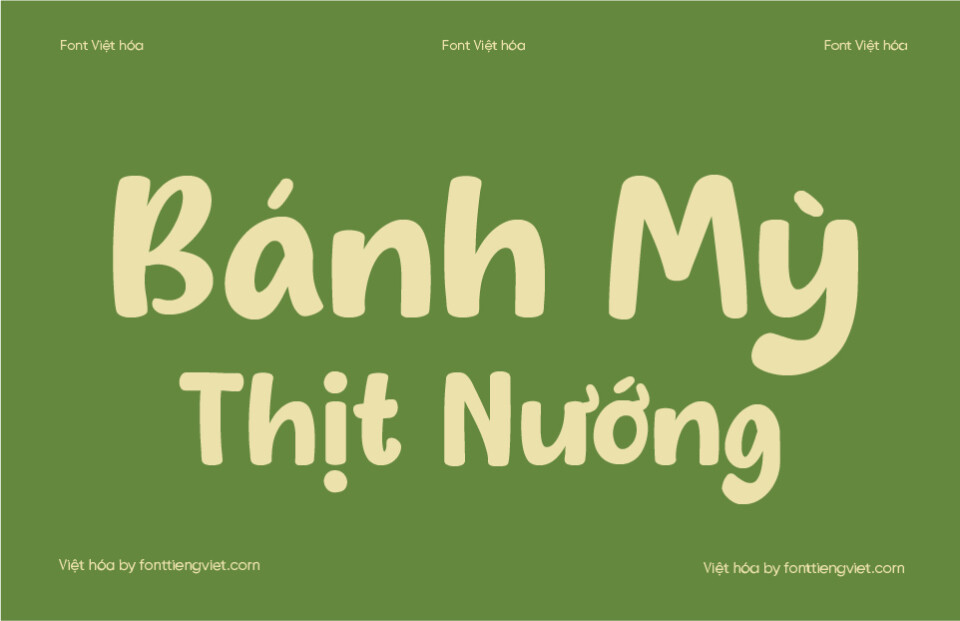
Font Việt hóa 1FTV VIP Season Prime Đẳng Cấp Cho Thiết Kế Chuyên Nghiệp
Giới thiệu về Font Việt hóa 1FTV VIP Season Prime
Trong thế giới thiết kế đồ họa hiện đại, việc lựa chọn một Font Chữ phù hợp đóng vai trò quyết định đến tính thẩm mỹ và thông điệp của sản phẩm. Font Việt hóa 1FTV VIP Season Prime là một bộ phông chữ cao cấp, được tinh chỉnh kỹ lưỡng để phục vụ cộng đồng designer tại Việt Nam. Với phong cách hiện đại, thanh lịch và đường nét dứt khoát, bộ font này không chỉ mang lại vẻ ngoài chuyên nghiệp mà còn đảm bảo tính ứng dụng cao trên nhiều nền tảng khác nhau.
Đặc điểm nổi bật của bộ font
Bộ Font Việt hóa 1FTV VIP Season Prime sở hữu hệ thống ký tự đa dạng, hỗ trợ đầy đủ dấu tiếng Việt mà không gặp lỗi hiển thị. Cấu trúc chữ được thiết kế cân đối, tạo cảm giác dễ nhìn và sang trọng. Đây là lựa chọn lý tưởng cho các dự án thiết kế thương hiệu, làm tiêu đề tạp chí hoặc các ấn phẩm quảng cáo cần sự đột phá. Sự kết hợp giữa nét cổ điển và xu hướng tương lai giúp bộ font này luôn giữ được sức hút riêng biệt.
Ứng dụng Font Việt hóa 1FTV VIP Season Prime trong thực tế
Lợi ích khi sử dụng font trong giáo dục và sáng tạo
Đối với học sinh và giáo viên, việc sử dụng các phông chữ rõ ràng như 1FTV VIP Season Prime giúp các bài thuyết trình và tài liệu học tập trở nên sinh động, dễ tiếp thu hơn. Trong lĩnh vực truyền thông, bộ font này hỗ trợ tối ưu cho việc tạo nội dung trên mạng xã hội, giúp thông điệp truyền tải đến khán giả một cách ấn tượng. Khả năng tương thích tốt trên cả phần mềm máy tính lẫn ứng dụng di động là một điểm cộng lớn.
Kết luận về bộ font chất lượng cao
Hy vọng rằng bộ Font Việt hóa 1FTV VIP Season Prime sẽ trở thành công cụ đắc lực, khơi nguồn cảm hứng cho những ý tưởng sáng tạo mới mẻ của bạn. Việc sở hữu một bộ Font Miễn Phí, Font Việt Hóa, Font Việt hóa 1FTV VIP Season Prime chất lượng sẽ giúp nâng tầm giá trị hình ảnh một cách hiệu quả nhất.